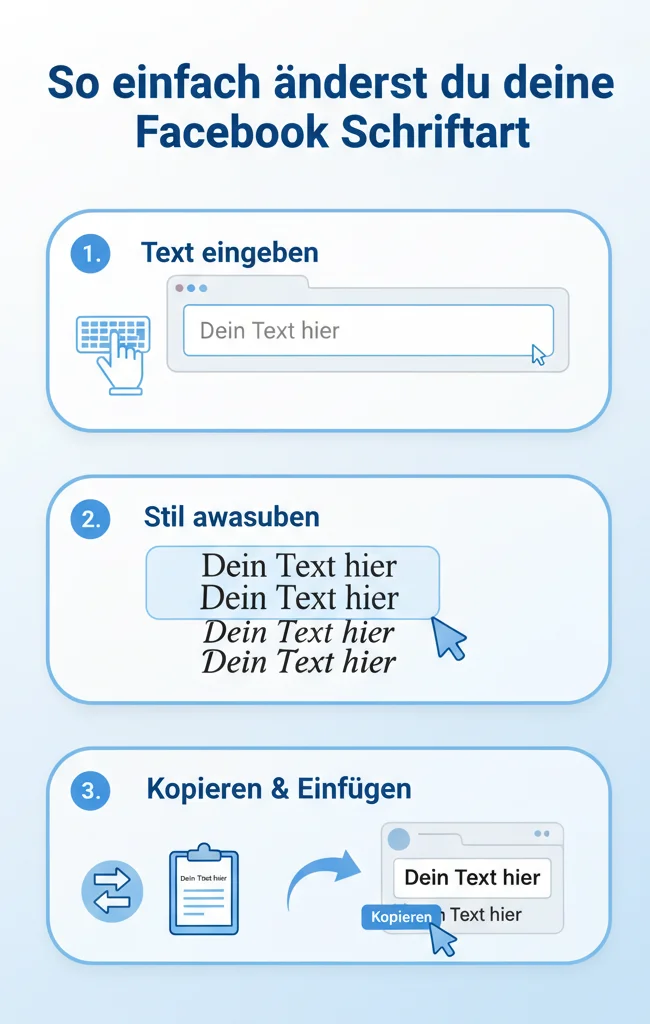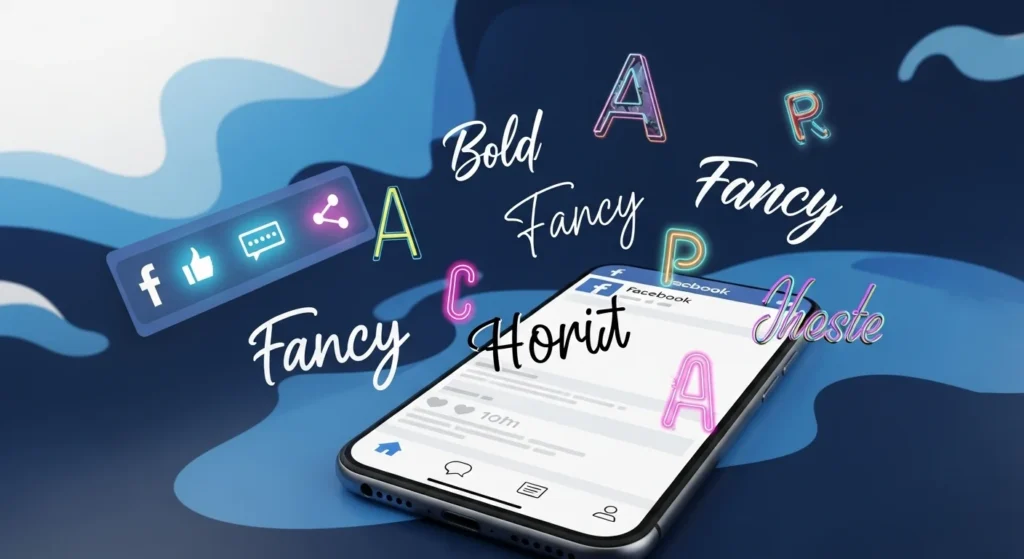
Ideen für fette Schrift und Namen für Biografie und Beiträge
Willst du, dass deine Facebook-Posts, Kommentare oder dein Profil-Name aus der Masse herausstechen? Mit unserem Facebook Schrift Generator kannst du deinen Text sofort in Dutzende von einzigartigen und coolen Stilen umwandeln. Kopiere deine neue Facebook Schrift einfach mit einem Klick und füge sie direkt in deinem Profil, deiner Bio oder deinem neuesten Beitrag ein. Es ist kostenlos, schnell und funktioniert überall.
So einfach änderst du deine Facebook Schrift Generator
Text eingeben: Tippe oder füge deinen gewünschten Text in das obere Feld unseres Generators ein.
Stil auswählen: Scrolle durch die Liste der automatisch generierten Facebook Schriften. Du findest alles von kursiv über serifenbetont bis hin zu ausgefallenen Symbol-Schriften.
Kopieren & Einfügen: Klicke auf “Kopieren” neben deinem Lieblingsstil. Gehe dann zu Facebook und füge den Text an der gewünschten Stelle ein (z. B. in einem neuen Beitrag, einem Kommentar oder in deiner Profil-Bio).
Warum eine andere Schriftart auf Facebook nutzen?
Facebook verwendet standardmäßig eine einheitliche Schriftart für die gesamte Plattform. Das sorgt für ein sauberes Erscheinungsbild, macht es aber auch schwer, visuell aufzufallen.
Die Verwendung einer speziellen facebook schrift generator ist der einfachste Weg, um Aufmerksamkeit zu erregen, wichtige Punkte hervorzuheben oder deiner Persönlichkeit Ausdruck zu verleihen.
Für dein Profil, deine Bio und Facebook Namen
Dein Facebook-Name und deine Profil-Bio sind das Erste, was Besucher sehen. Mit einer einzigartigen Schriftart kannst du einen unvergesslichen ersten Eindruck hinterlassen. Unser Tool ist auch perfekt, wenn du nach Facebook Namen Ideen suchst, die wirklich herausstechen.
Posts und Kommentare hervorheben
Egal ob du eine Ankündigung machst, ein Zitat teilst oder einfach nur einen Kommentar witziger gestalten möchtest – eine andere Schriftart kann den Unterschied machen. Formatiere deinen Text, um deine Follower zum Anhalten und Lesen zu bewegen.
Facebook Fett Schreiben: Der einfachste Weg
Viele Nutzer suchen gezielt nach einer Möglichkeit, auf Facebook fett zu schreiben, um wichtige Informationen hervorzuheben. Die Standardfunktionen von Facebook machen dies in Posts oder Kommentaren oft unmöglich.
Unser Facebook Schrift Generator löst dieses Problem.
Tippe einfach deinen Text ein, und du wirst in den Ergebnissen mehrere “fette” Versionen (z. B. serifenbetont fett oder serifenlos fett) finden. Diese kannst du, genau wie alle anderen Stile, einfach kopieren und einfügen. Es ist der schnellste Weg, um Text auf Facebook “fett” zu formatieren, ohne spezielle Codes zu benötigen.
[Bild, das einen normalen Text zeigt, der vom Tool in fettgedruckten Text umgewandelt wird]
Wie funktioniert der Schriftgenerator? (Das Unicode-Geheimnis)
Du fragst dich vielleicht, wie das technisch funktioniert, wenn Facebook doch gar keine anderen Schriftarten erlaubt?
Die Antwort lautet: Unicode. Unser Generator wandelt deine normalen Buchstaben (A, B, C) nicht in eine Schriftart um, sondern in spezielle Unicode-Zeichen, die aussehen wie andere Buchstaben (z. B. 𝔸, 𝔹, ℂ oder 𝔄, 𝔅, ℭ).
Da es sich um Standard-Textzeichen handelt, kann Facebook (und auch Instagram, Twitter, TikTok usw.) diese problemlos anzeigen. Es ist im Grunde derselbe Trick, mit dem auch Emojis (wie ✨ oder 👍) funktionieren.
Ja, absolut! Unser Tool ist zu 100 % kostenlos. Du kannst so viele Texte generieren und kopieren, wie du möchtest.
Ja. Unsere Website ist vollständig mobilfreundlich. Du kannst den Schriftgenerator direkt in deinem Handy-Browser öffnen, den Text kopieren und ihn sofort in deiner Facebook-App einfügen.
Das passiert, wenn dein Gerät oder Browser ein bestimmtes Unicode-Zeichen nicht in seiner Bibliothek hat. Es ist selten, kann aber bei sehr alten Geräten oder Betriebssystemen vorkommen. Lösung: Wähle in diesem Fall einfach einen anderen, gängigeren Stil aus unserer Liste aus. Fette und kursive Stile funktionieren fast immer.
Ja! Viele der generierten Stile enthalten auch spezielle Facebook Zeichen und Symbole, die du zusammen mit deinem Text kopieren kannst, um deinen Namen oder deine Beiträge weiter zu verzieren.